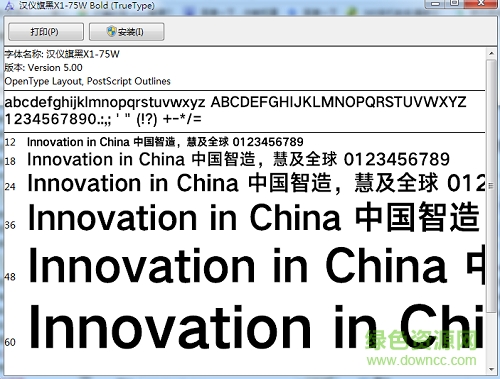
漢儀旗黑75w ttf是一款非常有個性的漢儀字體,這款黑體字體設(shè)計簡約、爽朗富有時代氣息,看上去非常的大方、美觀,有喜歡的朋友歡迎來綠色資源網(wǎng)下載!
漢儀旗黑75w是漢儀旗黑系列字體中的一款,筆畫設(shè)計中融入了書寫的韻味,采用陰陽線的處理方法,講究線條之美,使筆劃挺拔有力,剛?cè)嵯酀?/p>